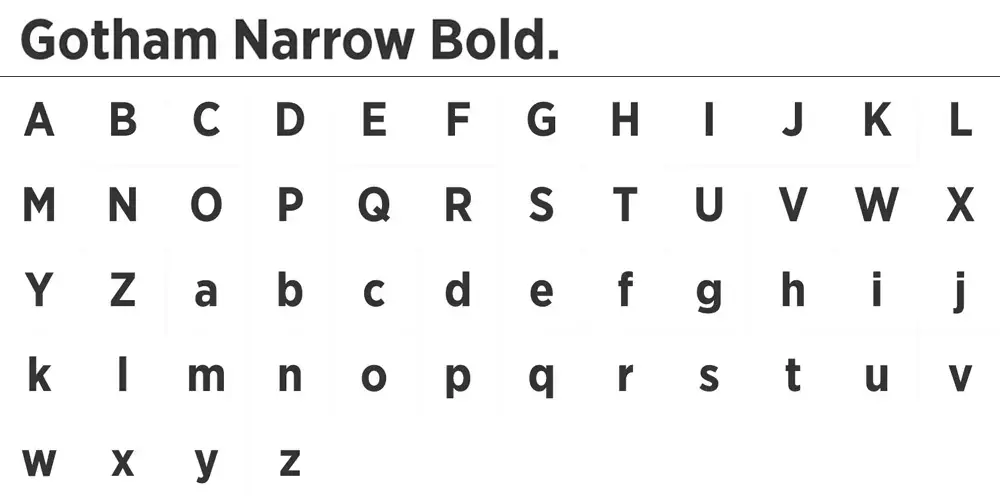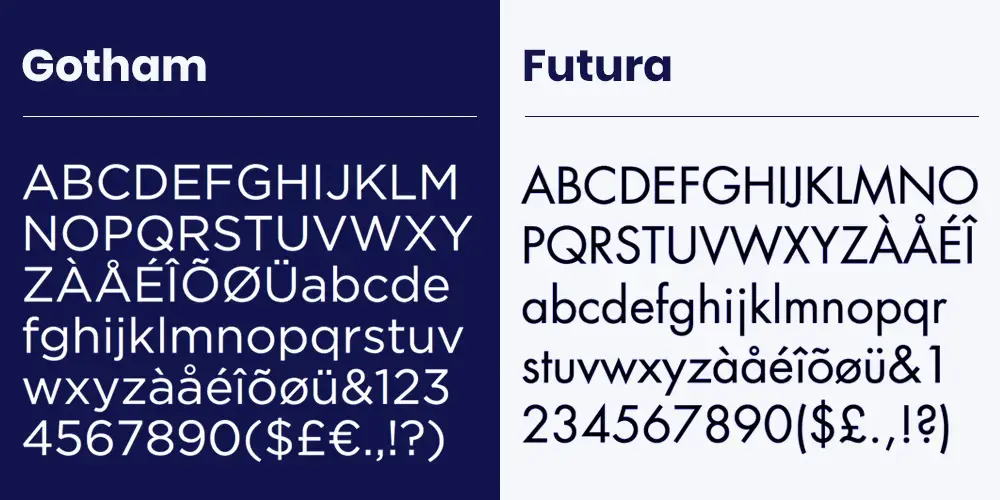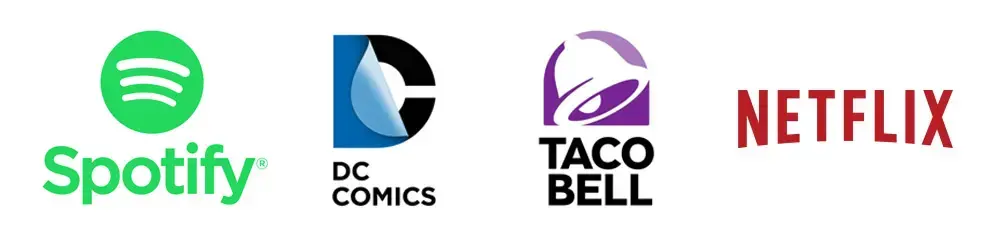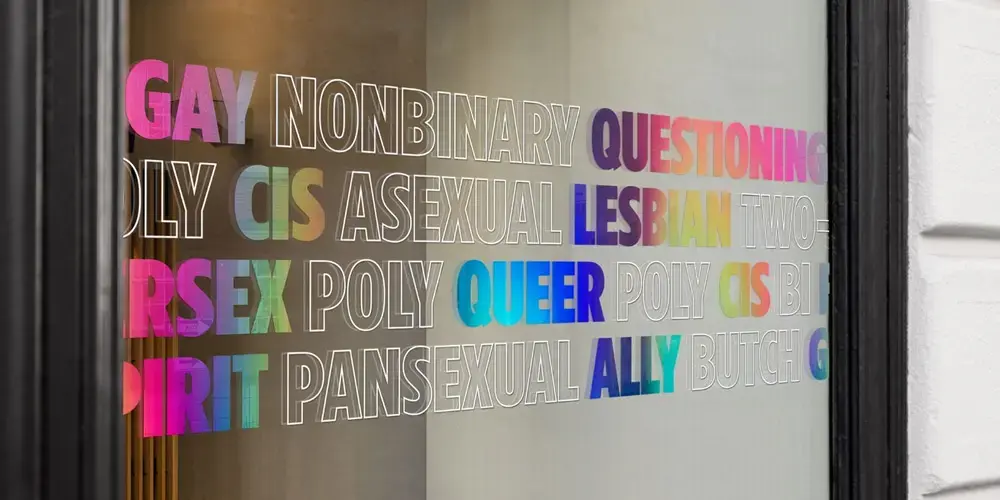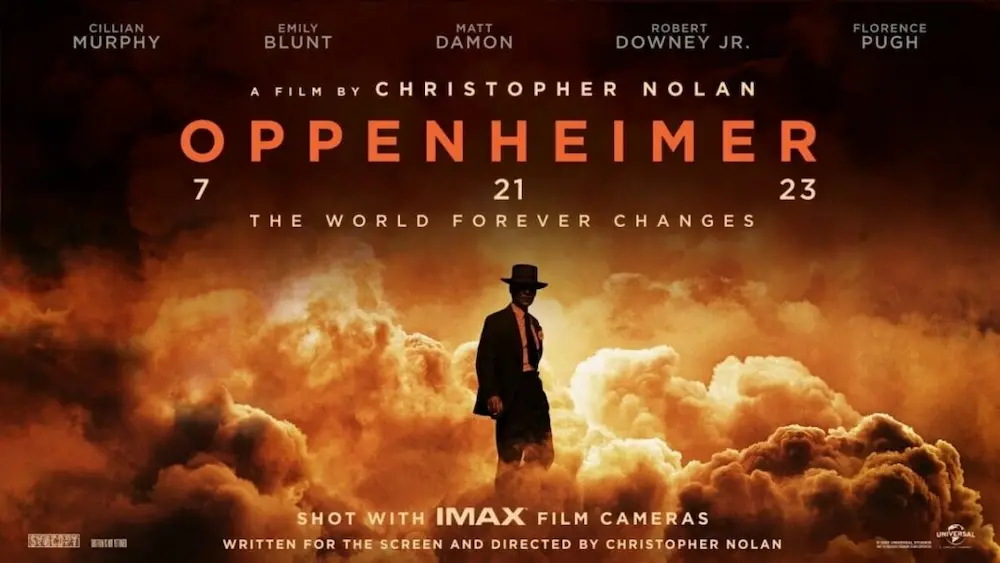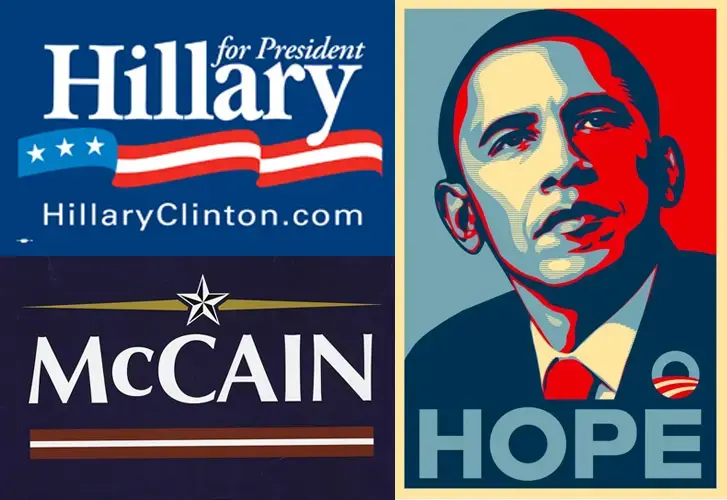
Oppenheimer, le choix d’une typo atomique
Après la Franklin Gothic pour Batman, l'Avenir Black pour Inception, le réalisateur Christopher Nolan brandit une fois de plus l'étendard des typos sans empattement, grasses et en capitale pour identifier son nouveau film Oppenheimer. Place cette fois à la font Gotham Narrow Bold ! NON, il ne s’agit pas JUSTE d’une autre font sans sérif. Parce que choisir une font Gotham pour Oppenheimer, c’est faire le choix d’une identité résolument new-yorkaise pour évoquer le projet Manhattan.
Gotham Narrow Bold, la font new-yorkaise
La font Gotham a été créée en 2000 par Tobias Frere-Jones et publiée par la fonderie Hoefler & Co, société de son ancien partenaire commercial Jonathan Hoefler. C’est à l’origine, le magazine GQ qui commande une linéale géométrique, "masculine, nouvelle et fraîche" afin de crédibiliser leur image.
Et c’est finalement de ses déambulations dans les rues de Manhattan, armé de son appareil photo, que Frere-Jones puisa son inspiration. Notamment du lettrage d’anciens bâtiments, "pour préserver ces vieux morceaux de New York qui pourraient être effacés avant d'être appréciés”.
Inspirée des polices des années 20 telle que la Futura qui affirmait la volonté d’un retour à l’essentiel, en se débarrassant des fioritures et se focalisant sur la géométrie, cette image new-yorkaise se veut plus proche de l'ingénieur que du typographe.
Et bien qu’on pourrait croire que toutes les typo géométriques sont les mêmes, il n’en est rien !
La légendaire police Futura est un modèle de géométrie dans les écoles de graphisme, la police Gotham affiche elle une chasse plus uniforme, lui donnant un air plus rond et moins piquant. Ce qui, malgré une inspiration historique, apporte une modernité aux caractères.
Le journaliste Andrew Romano déclare que "Contrairement aux autres polices de caractères sans empattement, ce n'est pas allemand, ce n'est pas français, ce n'est pas suisse. C'est très américain."
C’est donc sans surprise que la typo apparaît en 2008 dans la campagne présidentielle de Barack Obama, s’opposant à la révérencieuse New Baskerville d’Hillary et l’Optima de McCain (aussi utilisée pour le Vietnam Veterans Memorial).
Pour la grosse pomme, c’est aussi la typo de la pierre angulaire du One World Trade Center et la police officielle de l’Université de New-York.
Avec ses quatres chasses et ses huit graisses, l'éventail des possibilités graphiques est énorme. De nombreuses marques l’adoptent : Taco Bell, DC Comics, Spotify... Jusqu’en 2018 elle représente Netflix (avant que la marque crée sa propre police pour des raisons commerciales).
En 2009, les versions Narrow et Extra Narrow sont introduites.
L’adaptabilité de la new-yorkaise est sans limite. En 2011, son créateur va jusqu’à annoncer la possibilité d’ajout d’empattement dans le cadre de la campagne présidentielle. Il écrit : “Pouvons-nous ajouter des empattements à Gotham ? Pour le président des États-Unis ? Oui, nous le pouvons.”
Histoire et audace de la font Gotham
Écho contemporain d’un vieux New-York, et succès commercial, la font Gotham semble pouvoir tout faire, tout montrer. Elle exprime un éventail de voix aussi large que possible. Et c’est dans ce sens, qu’elle est choisie en 2022 pour accompagner la Knockout dans la nouvelle identité de la NYC Pride.
Mais alors, quel rapport avec Oppenheimer ?
Oppenheimer c’est l’histoire du Projet Manhattan. C’est un drame humain, et politique. Le reflet coup de poing d’une société d’après-guerre et un blockbuster hollywoodien. Et tout ça, c’est terriblement Gotham !
Avec une chasse étroite, une pincée de bold, des caractères capitale, on est tout de suite propulsé dans un univers froid et grave. C’est simple, déjà vu mais ça fait l’effet d’une bombe.
Pari réussi pour les équipes d’Universal Pictures.
Les alternatives gratuites à la police Gotham
Bien sûr, la font Gotham est une typo sous licence et son prix peut en freiner plus d’un. Heureusement, il existe de très correctes alternatives gratuites !
Metropolis
Quel joli clin d'œil de proposer une alternative à la police Gotham nommée Metropolis ! Il s’agit de la font la plus proche et bien qu’elle offre moins de déclinaisons que sa grande sœur, elle nous gratifie tout de même des huit graisses disponibles.
Montserrat
Vous travaillez dans le web, vous avez besoin d’une font simple à intégrer et une valeur sûre pour tous les navigateurs : tournez vous vers une Google Font. La Montserrat n’est pas strictement identique. Les traits sont moins subtils, la lettre “a” plus aplatie, mais en dehors des puristes, elle fait parfaitement illusion !